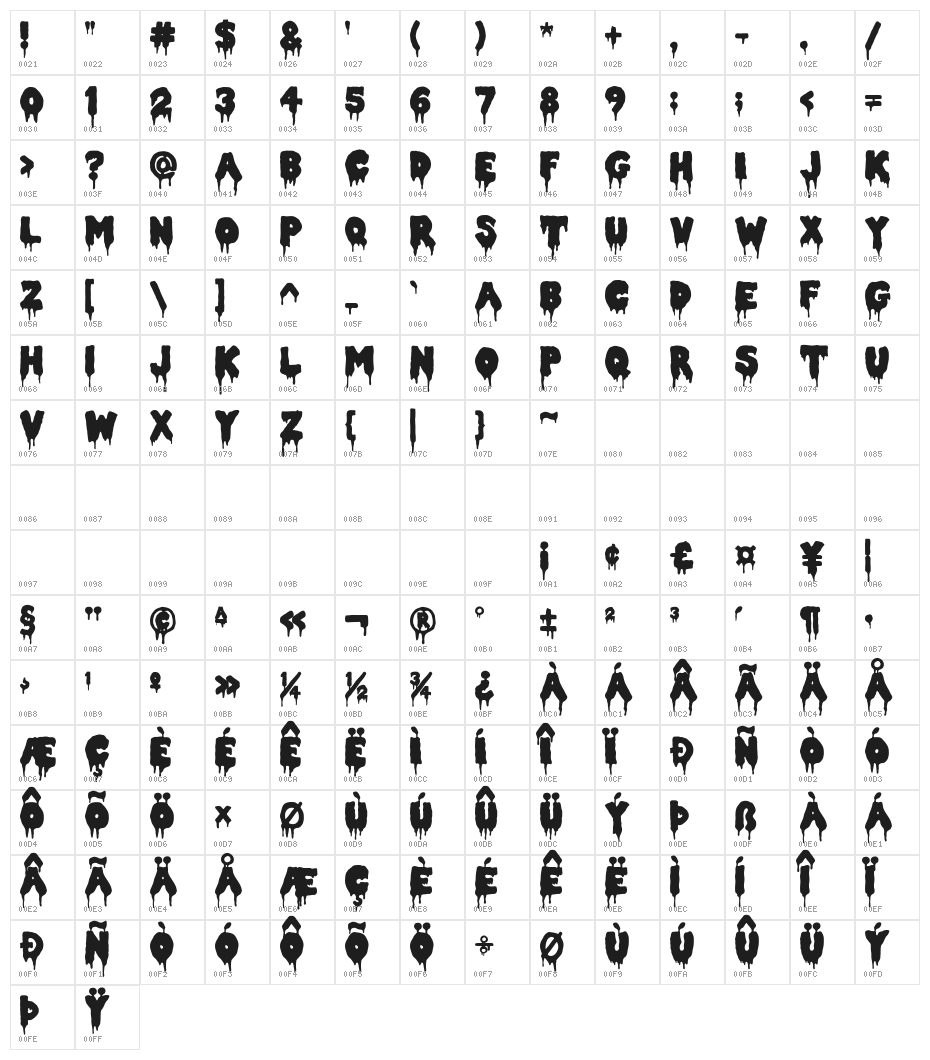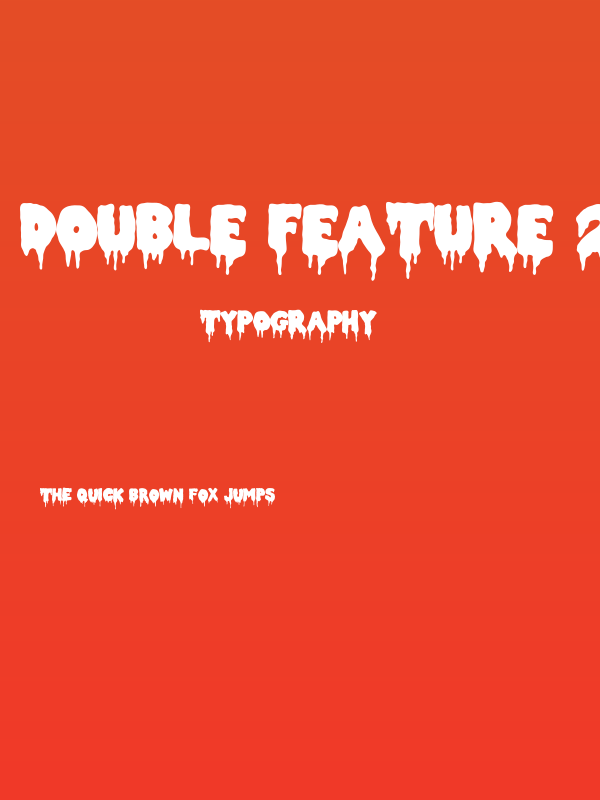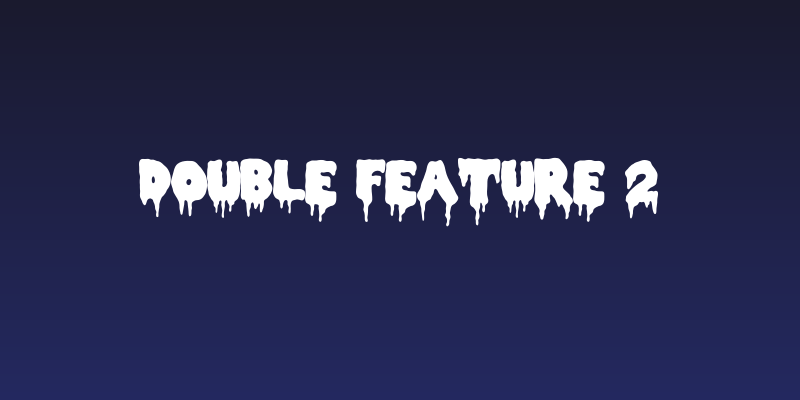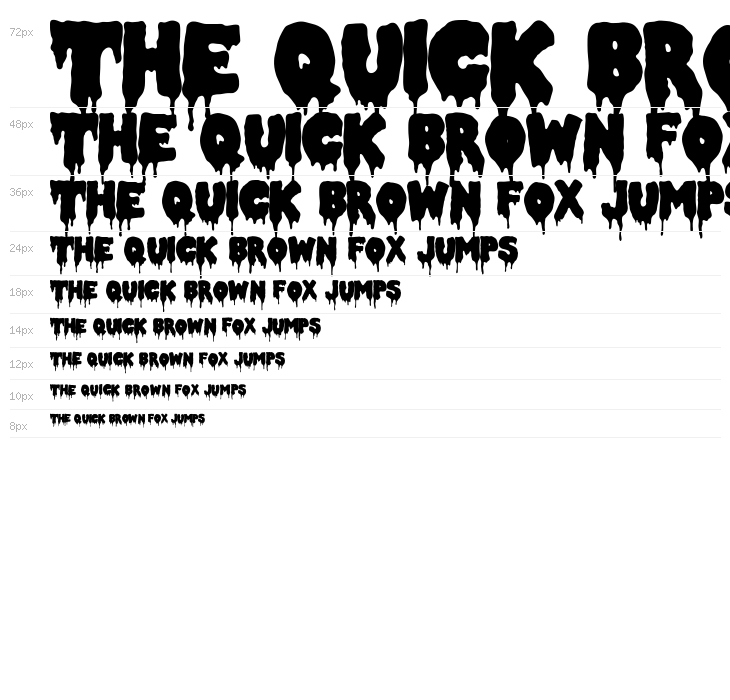
Double Feature 2 Font
| Caso d'uso | Headlines, Posters, Logos |
| Progetti proposti | Ideal for Halloween posters, horror movie titles, themed event invitations, and graphic designs that require a dramatic and eerie touch. |